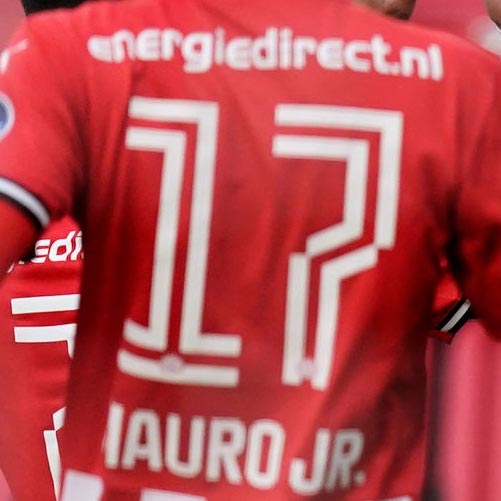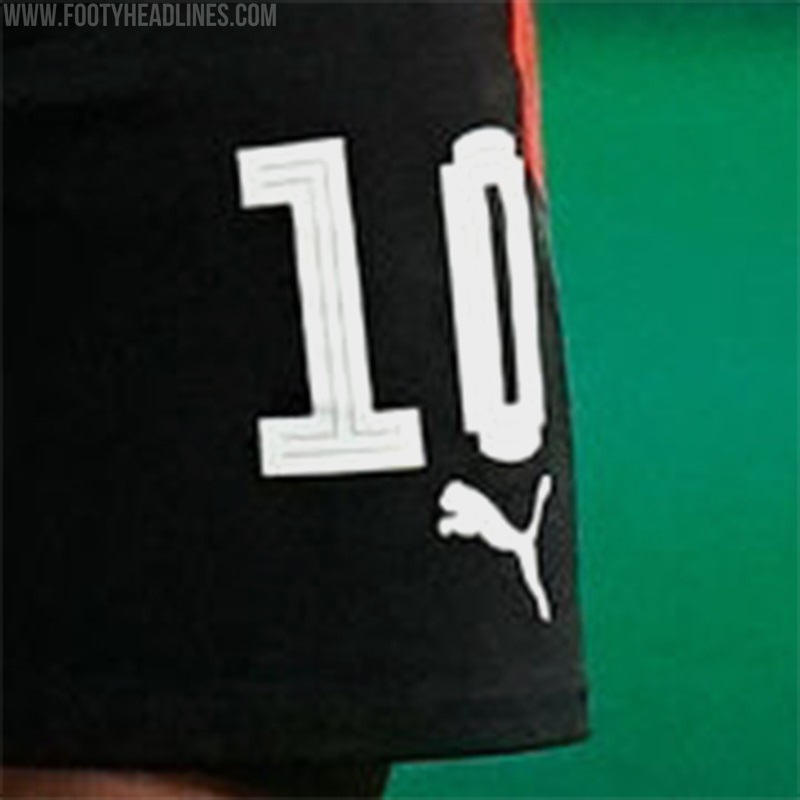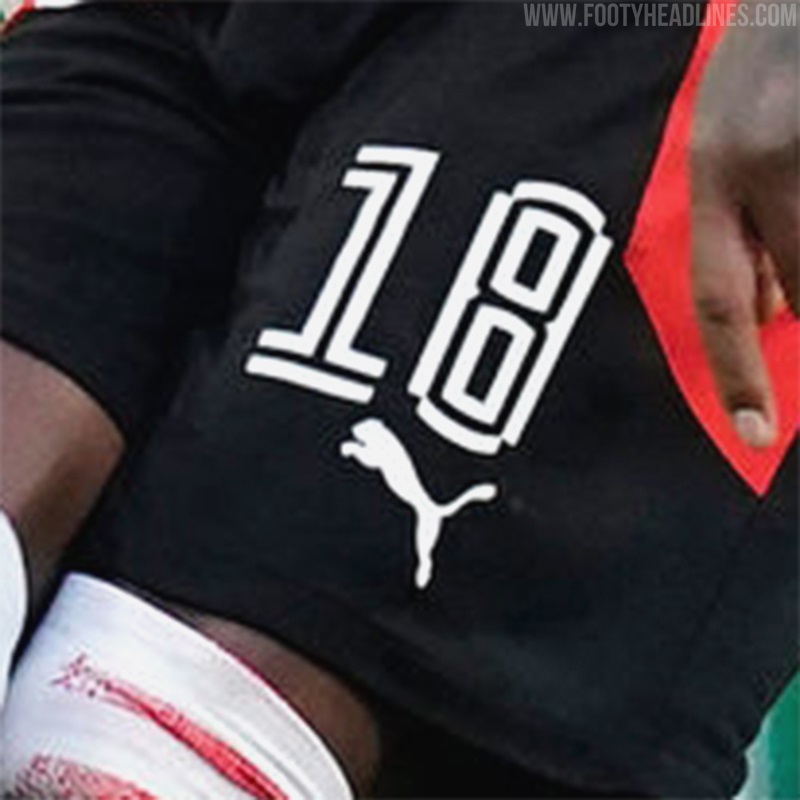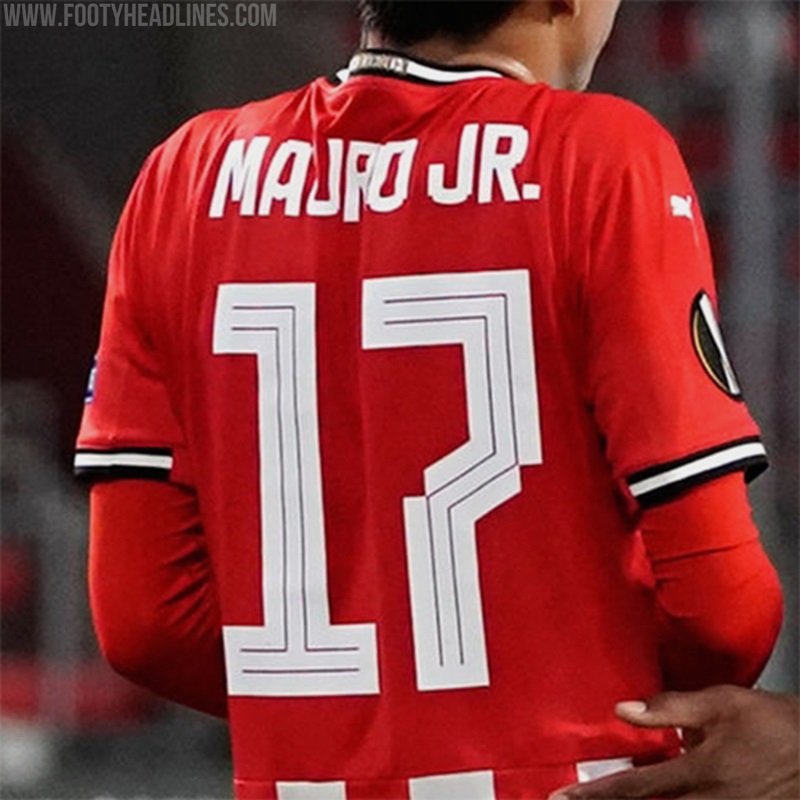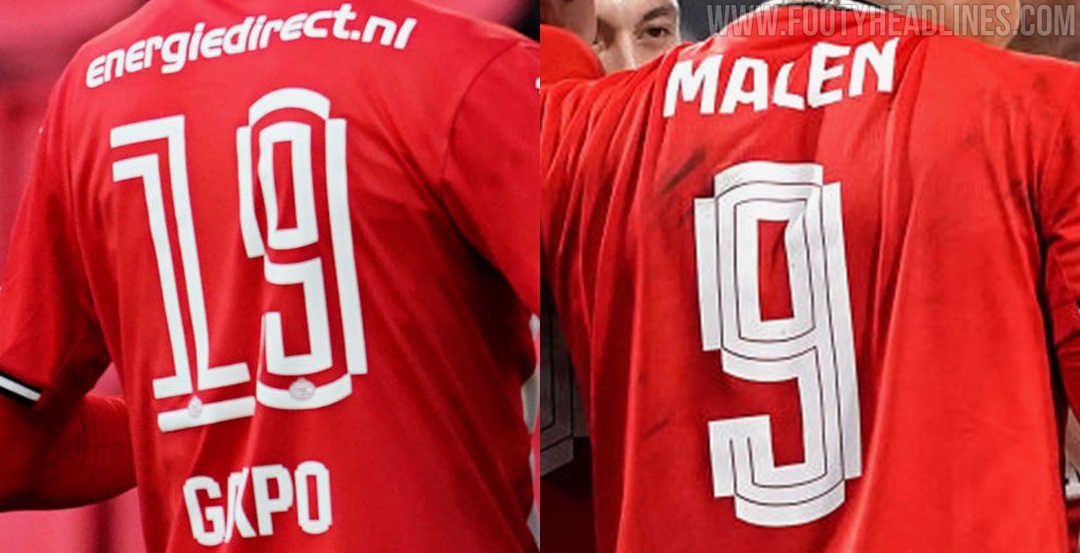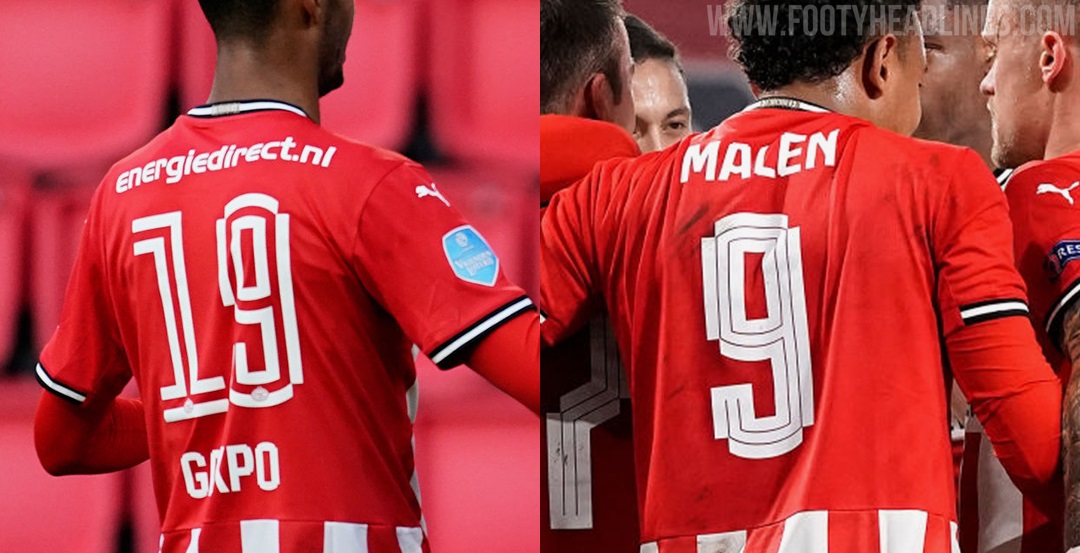
Genau wie Real Madrid: PSV Eindhoven wird von UEFA gezwungen Trikot-Schriftart zu verändern
Im Anschluss an unseren Bericht über Real Madrid, die in der UEFA Champions League eine modifizierte Trikot-Schriftart trugen, machte uns ein Follower darauf aufmerksam, dass auch die niederländische Mannschaft Eindhoven ihre Trikot-Schriftart aktualisieren musste, um den UEFA-Ausrüstungsvorschriften zu entsprechen.
PSV Eindhoven trägt in Europa League eine modifizierte Trikot-Schriftart
Die PSV Eindhoven 20-21 Trikots sind mit einer brandneuen Trikot-Schrift ausgestattet, die einen bemerkenswerten Stil aus getrennten Linien aufweist. Die PSV 20-21 Trikot-Schrift verstößt jedoch gegen die UEFA-Regeln über die Linienstärke von Trikot-Schriften und musste daher geändert werden.
Die UEFA PSV 20-21 Trikot-Nummern haben die gleiche Form, verzichten aber auf den großen Freiraum, um der UEFA-Regel zu entsprechen, wonach Linien nicht dicker als 2 mm sein dürfen.
Die UEFA-Ausrüstungsvorschrift 10.08: "Die Nummern dürfen Atmungslöcher oder Linien bis zu 2 mm Breite enthalten und sie dürfen in bis zu drei Teile geteilt werden, sofern die Teilungen 2 mm nicht überschreiten".
In der niederländischen Liga sind die PSV-Nummern erlaubt.
Einzigartige PSV Eindhoven 20-21 Trikot-Schriftart veröffentlicht